Valentine T-shirt Typography Design
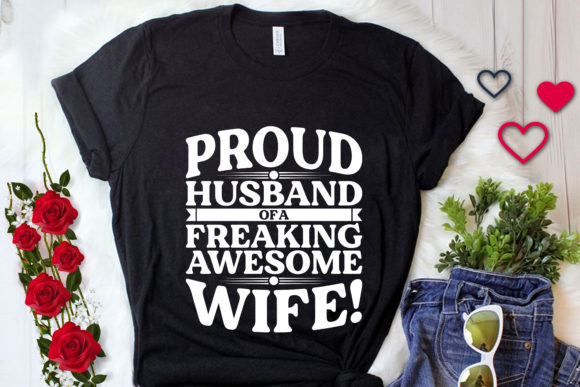
Att hitta rätt designelement kan vara utmanande, men Valentine T-shirt Typography Design erbjuder en exceptionell samling som omedelbart lyfter ditt arbete.
Oavsett om du skapar POD-produkter (Print on Demand), bröllopsinbjudningar eller grafik för sociala medier, är Valentine T-shirt Typography Design ett perfekt val.